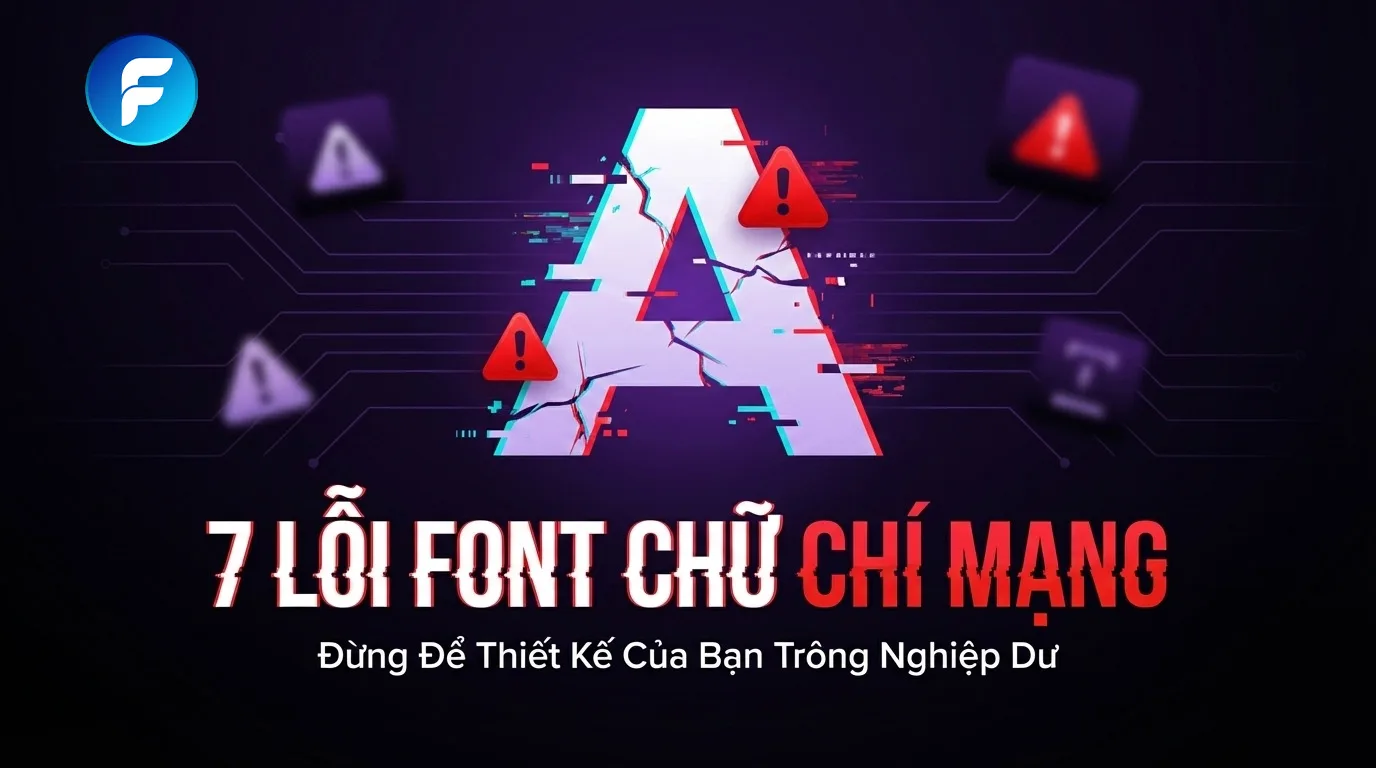
7 Lỗi “Chí Mạng” Khi Sử Dụng Font Chữ Khiến Thiết Kế Của Bạn Trông Nghiệp Dư
Bạn đã bao giờ nhìn vào một tấm poster, một trang web hay một tấm danh thiếp và cảm thấy có điều gì đó “sai sai” dù hình ảnh rất đẹp? Rất có thể, thủ phạm chính là cách sử dụng font chữ.
Typography (nghệ thuật chữ) không chỉ là việc chọn một font đẹp mắt. Nó là sự cân bằng tinh tế giữa thẩm mỹ và công năng. Một lỗi nhỏ trong việc dùng font có thể biến một thiết kế chuyên nghiệp thành một sản phẩm nghiệp dư chỉ trong nháy mắt.
Hãy cùng điểm qua 7 lỗi phổ biến nhất mà rất nhiều người (thậm chí cả designer) mắc phải và cách khắc phục chúng nhé!
1. “Bữa Tiệc” Quá Đông Đúc: Dùng Quá Nhiều Font Chữ
Đây là lỗi kinh điển nhất của người mới bắt đầu. Vì muốn thiết kế trông phong phú, bạn kết hợp 4-5 loại font khác nhau trong một không gian nhỏ. Kết quả là một “nồi lẩu thập cẩm” gây rối mắt và mất tập trung.
- Hậu quả: Người xem không biết đâu là thông tin quan trọng nhất và cảm thấy thiết kế thiếu sự nhất quán, chuyên nghiệp.
- Giải pháp: Hãy tuân thủ quy tắc “Tối đa 2-3 font”. Một font cho tiêu đề chính để tạo điểm nhấn, và một font khác (dễ đọc hơn) cho nội dung chi tiết là đủ. Sự đơn giản chính là đỉnh cao của sự tinh tế.
2. Thảm Họa Kerning: Khi Khoảng Cách Gây Hiểu Lầm
Kerning là việc điều chỉnh khoảng cách giữa hai ký tự đơn lẻ. Nghe có vẻ tiểu tiết, nhưng kerning tồi có thể dẫn đến những tai nạn “dở khóc dở cười”.
- Hậu quả: Các chữ cái dính vào nhau tạo thành từ khác, hoặc tách quá xa làm đứt mạch đọc. Ví dụ nổi tiếng là chữ “CLICK” nếu kerning tồi giữa ‘C’ và ‘L’ sẽ trông giống như… một từ nhạy cảm khác.
- Giải pháp: Đừng tin tưởng tuyệt đối vào chế độ auto-kerning của phần mềm. Hãy luôn kiểm tra lại bằng mắt thường, đặc biệt là với các tiêu đề lớn và logo. Hãy đảm bảo khoảng không gian giữa các con chữ trông cân bằng và hài hòa.
3. “Đánh Đố” Thị Giác: Dùng Font Script Cho Đoạn Văn Dài
Font Script (chữ viết tay) rất đẹp, bay bướm và sang trọng. Nhưng nó sinh ra không phải để dành cho những đoạn văn dài.
- Hậu quả: Các nét chữ uốn lượn chồng chéo lên nhau khi ở kích thước nhỏ và mật độ dày đặc, khiến người đọc phải “căng mắt” để dịch từng chữ. Điều này gây mỏi mắt và ức chế.
- Giải pháp: Chỉ sử dụng Font Script cho các tiêu đề ngắn, lời đề tựa hoặc điểm nhấn để tạo sự sang trọng. Đối với nội dung chính (body text), hãy luôn ưu tiên các font Serif hoặc Sans-serif sạch sẽ, dễ đọc.
4. “Tra Tấn” Con Chữ: Kéo Dãn Hoặc Bóp Méo Font
Khi một dòng chữ không vừa với không gian thiết kế, nhiều người có thói quen “tiện tay” kéo dãn chiều ngang hoặc bóp méo chiều dọc của nó.
- Hậu quả: Hành động này phá vỡ hoàn toàn tỷ lệ vàng và cấu trúc mà nhà thiết kế font đã dày công xây dựng. Các nét chữ trở nên dị dạng, mất thẩm mỹ và trông rất “rẻ tiền”.
- Giải pháp: Tuyệt đối không bao giờ bóp méo font chữ. Nếu cần điều chỉnh độ rộng, hãy sử dụng các biến thể (weights) khác của font đó (ví dụ: Condensed, Extended) hoặc đơn giản là chọn một font khác phù hợp hơn.
5. Tàng Hình: Thiếu Tương Phản Giữa Chữ Và Nền
Một dòng chữ màu xám nhạt trên nền trắng, hoặc chữ màu xanh dương trên nền đen… nghe có vẻ “nghệ”, nhưng lại là một thảm họa về trải nghiệm đọc.
- Hậu quả: Người xem không thể đọc được nội dung một cách dễ dàng, đặc biệt là trong điều kiện ánh sáng kém hoặc trên màn hình điện thoại nhỏ. Thông điệp của bạn bị “tàng hình”.
- Giải pháp: Luôn đảm bảo độ tương phản đủ mạnh giữa màu chữ và màu nền. Chữ đen trên nền trắng (hoặc ngược lại) luôn là lựa chọn an toàn và hiệu quả nhất. Hãy kiểm tra độ tương phản bằng các công cụ online nếu bạn không chắc chắn.
6. Không Có “Chủ – Tớ”: Bỏ Qua Phân Cấp Thị Giác (Hierarchy)
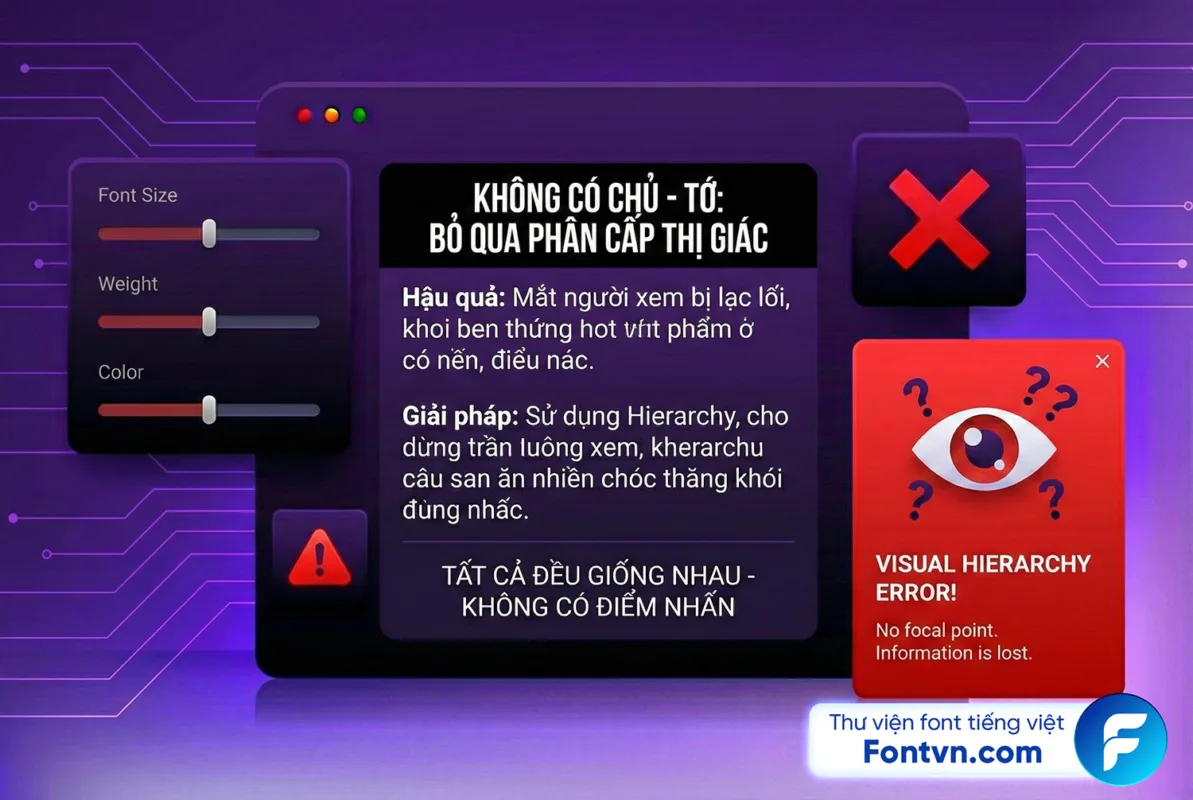
Nếu tất cả các dòng chữ trong thiết kế của bạn đều có cùng kích thước, màu sắc và độ đậm nhạt, thì đâu là điều quan trọng nhất bạn muốn người xem chú ý?
- Hậu quả: Mắt người xem sẽ bị lạc lối vì không có điểm neo. Họ sẽ lướt qua thiết kế của bạn mà không đọng lại thông tin gì.
- Giải pháp: Sử dụng Hierarchy (Phân cấp thị giác) để dẫn dắt mắt người xem. Tiêu đề chính phải to và nổi bật nhất. Tiêu đề phụ nhỏ hơn một chút. Nội dung chi tiết nhỏ nhất. Sử dụng màu sắc và độ đậm (bold) để tạo thêm các lớp ưu tiên.
7. “Râu Ông Nọ Cắm Cằm Bà Kia”: Chọn Sai “Giọng” Của Font
Như đã nói ở bài trước, mỗi font chữ đều có một “tính cách” riêng. Chọn sai tính cách sẽ tạo ra một sự mâu thuẫn nực cười.
- Hậu quả: Hãy tưởng tượng một tấm biển báo “Cấm Vượt” nguy hiểm nhưng lại được viết bằng font chữ Comic Sans ngộ nghĩnh. Nó sẽ làm giảm đi tính nghiêm trọng của thông báo. Hoặc một thiệp cưới sang trọng lại dùng font chữ điện tử (pixel) của thập niên 80.
- Giải pháp: Luôn tự hỏi: “Nội dung này mang cảm xúc gì?”. Nghiêm túc? Vui vẻ? Sang trọng? Hiện đại? Sau đó, hãy chọn một font chữ có “giọng điệu” tương ứng để truyền tải thông điệp đó một cách mạnh mẽ nhất.
Kết luận
Typography là một nghệ thuật đòi hỏi sự tinh tế và rèn luyện. Bằng cách tránh 7 lỗi cơ bản trên, bạn đã nâng tầm thiết kế của mình lên một bậc đáng kể. Hãy nhớ rằng, mục tiêu cuối cùng của font chữ không chỉ là để nhìn cho đẹp, mà là để truyền tải thông điệp một cách rõ ràng, mạch lạc và đầy cảm xúc.